字本身就是一种美,而字体则把这种美赋予更多的内涵。丰富多样的中文字体大全,能够满足不同的情景、情感、功能需求。一款中意的字体,能体现个性与品位。想要一些精美的中文字体,可以到哪里下载呢?
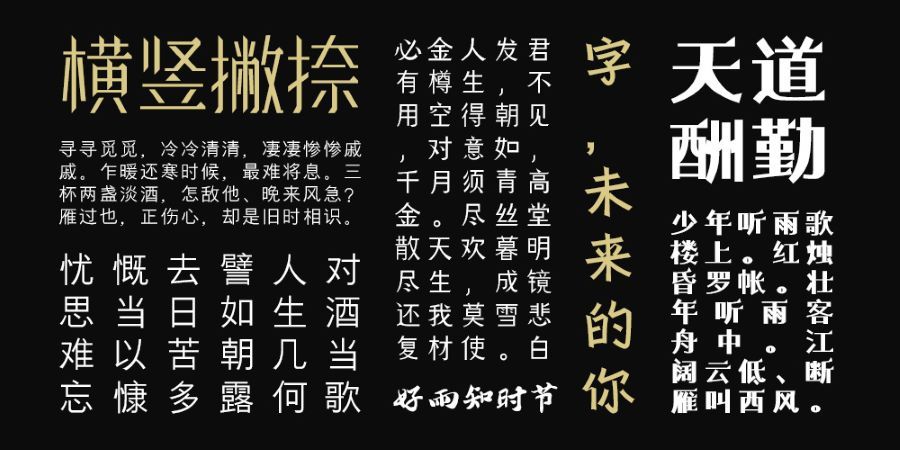
精美字体能带来什么?
从字体上可以看出一个人的精气神,有的是比较豪放,有的则显得比较婉约,有些显得比较刚毅,有些则比较潇洒。字体最早是写出来的,于是乎有了看字识人这一说法。然而,随着科技的不断发展,印刷术、激光技术以及网络的进步,越来越多的人开始在电脑上打字。
一款精美的字体,能够让人精神愉悦,交流更加顺畅,理解更加通畅。要知道,字本身在传播信息,通过视觉感知来表达情感。因此,字体具有功能性、美观性以及延展性等特性。于是,精美的字体不仅仅是能传情达意,而且能给人更深的体悟,融入具体的场景,讲述深层的故事。